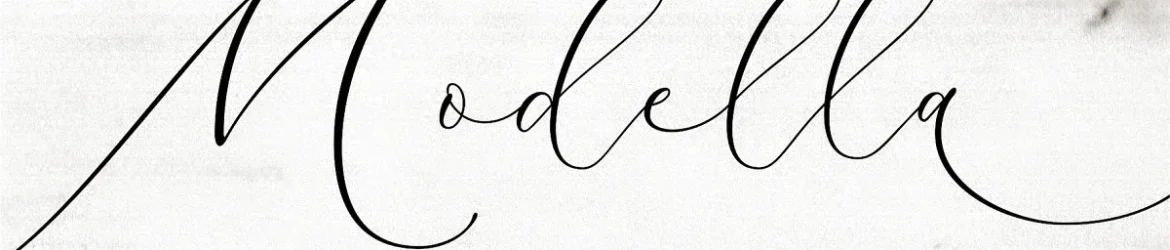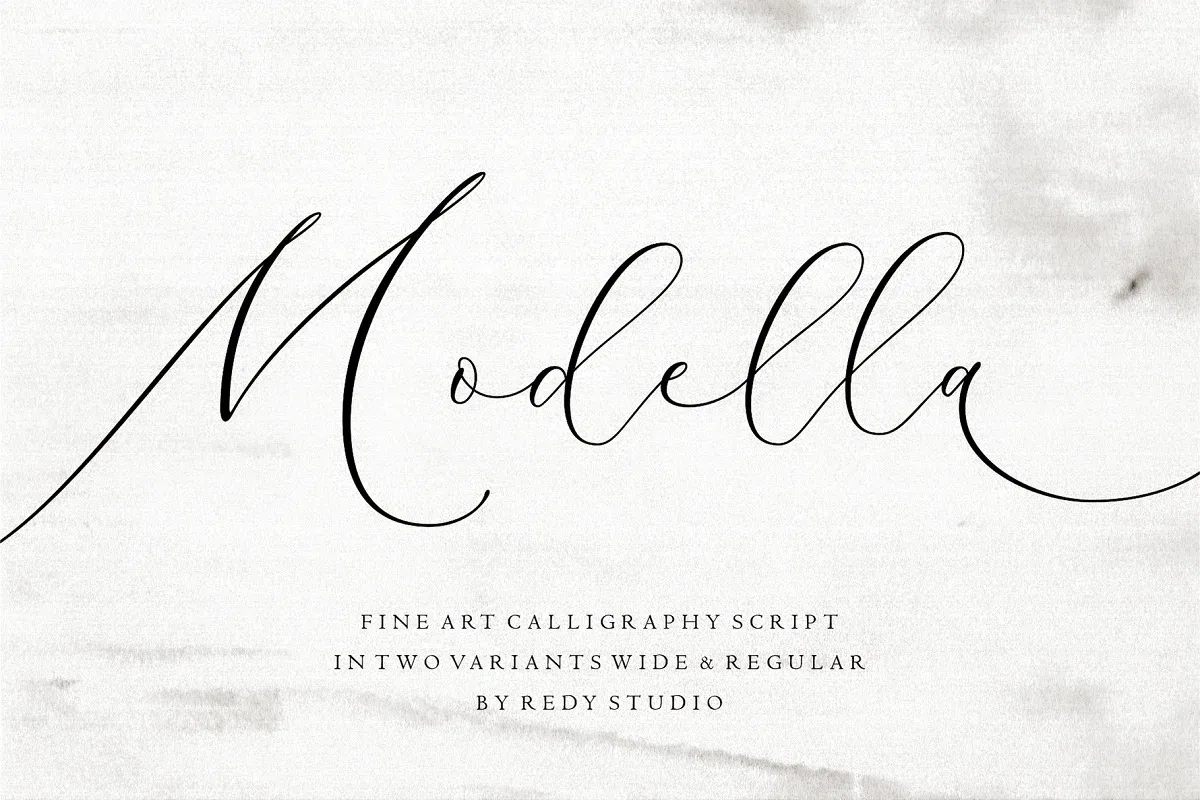
Modella Font
A Modella Font é uma elegante e delicada fórmula escrita à mão criada pela RedyStudio. Ideal para quem busca um toque sofisticado e personalizado em seus projetos, esta fonte oferece dois formatos (regular e estreito) com suas letras distintas e equilibradas, tornando-a verdadeiramente uma obra-prima do design de fóruns. Ademais, vem com suporte ligaduras, letras alternativas, e swashes para um toque único. Além disso, a Modella Font também inclui suporte internacional para mais de 70 idiomas ocidentais. Englobando tudo isso num só pacote, este é o tipo perfeito para designers que procuram uma fórmula criativa e versátil.